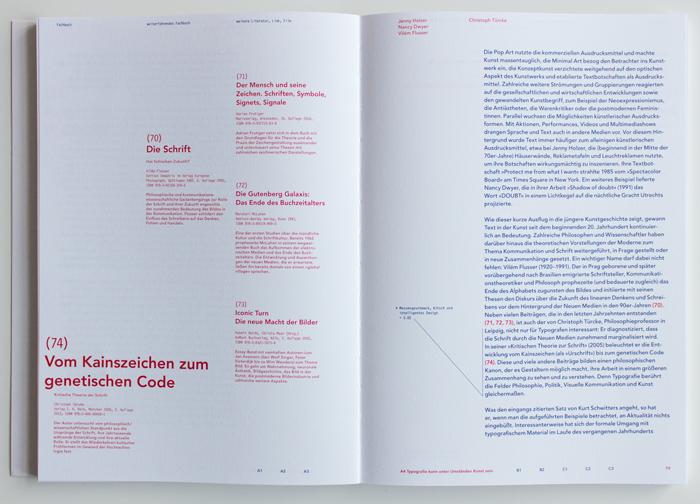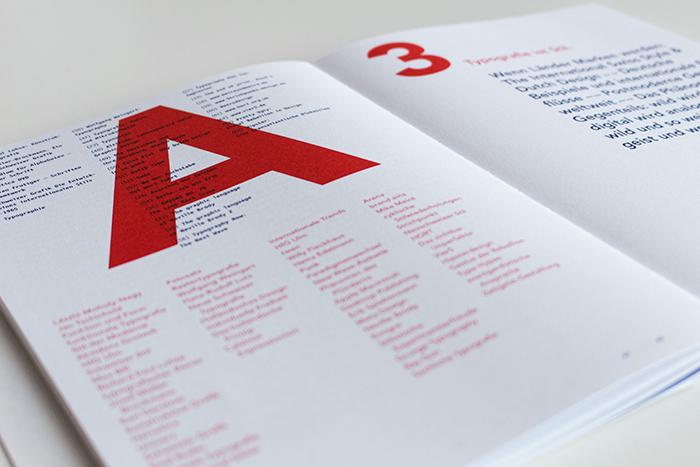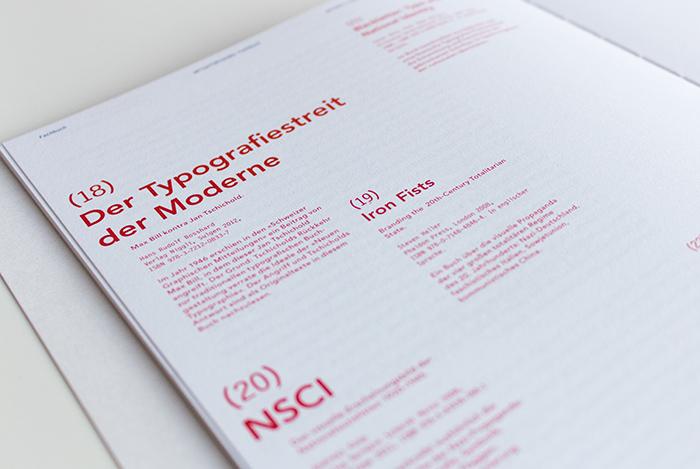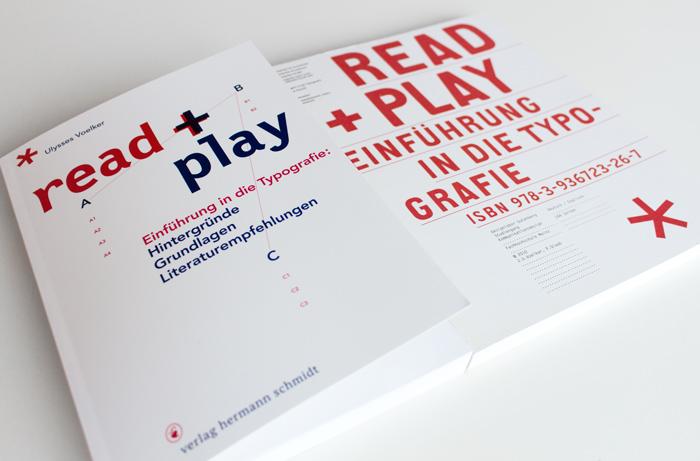
»Einführung in die Typografie: Hintergründe, Grundlagen, Literaturempfehlungen«. Mit diesem Untertitel ist im Hermann Schmidt Verlag Mainz das Buch »read + play« von Ulysses Voelker erschienen. Es handelt sich dabei um eine überarbeitete und erweiterte Fassung des gleichnamigen Werkes, das zuvor über das Designlabor Gutenberg der FH Mainz erschienen war.
Am Konzept hat sich auch mit der Neuauflage nichts Wesentliches geändert. Das Buch möchte ein »Navigationssystem« sein, das dem Leser hilft, sich die Welt der Typografie zu erschließen. In knappen, profunden Texten führt Ulysses Voelker in Funktion und Wirkung, Geschichte und Stile der Typografie ein und ergänzt jeden Einzelaspekt mit kommentierten und hierarchisierten Buchtipps. Anhand dieser Kurzeinführungen kann der Leser dann entscheiden, zu welchem Aspekt er sein Wissen in den weiterführenden Quellen vertiefen möchte.
Neue (links) und alte Ausgabe (rechts) nebeneinander
Bei der ersten Ausgabe hatte ich die etwas experimentelle Gestaltung kritisiert und dieser Punkt wurde in der Schmidt-Ausgabe spürbar verbessert. Zur weiterhin eingesetzten Letter Gothic gesellt sich nun die lesefreundlichere Avenir und auf die zwei Leserichtungen mit gedrehten Seiten wurde in der Neuausgabe verzichtet.